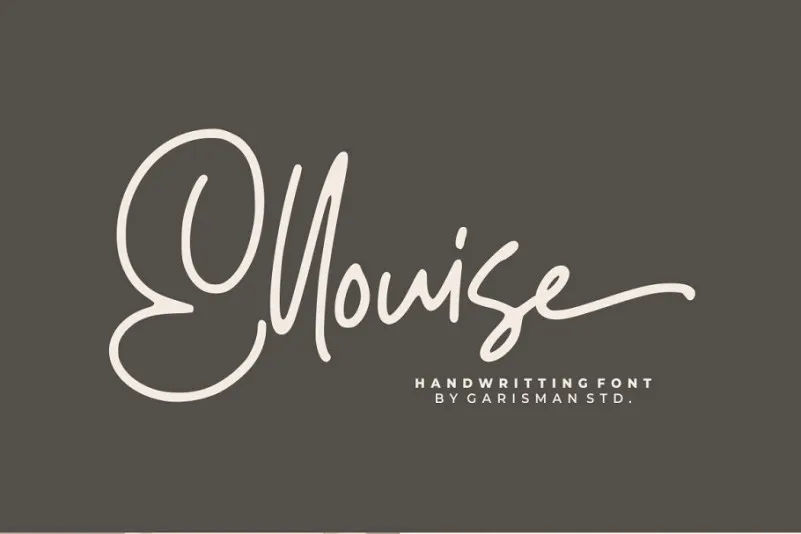
Ellouise Script Font – Fonte Grátis
Ellouise Script Font
Agradeço por dar uma olhada na Ellenise Font. Esta é uma fonte manuscrita natural e moderna. É perfeita para projetos que buscam um estilo autêntico, com suas curvas distintivas. É a escolha certa se você está procurando por uma mão-dura de escrita clássica que adicionará um charme irresistível aos seus logotipos, imagens da marca, frases, embalagens de produtos, materiais de merchandising e postagens nas redes sociais. Foi criada pelo designer Garisman Std. Ellouise Script é uma fonte moderna, natural, que entrega um script fresco e elegante, garantindo atração imediata para seus projetos visuais. Este design foi desenvolvido pela 0001themes e carrega um ar contemporâneo com suas curvas distintivas e características únicas. A Ellenise Script é uma excelente opção para aqueles que buscam incorporar um toque único de arte manuscrita em seus projetos visuais, tornando-os ainda mais atraentes e memoráveis.